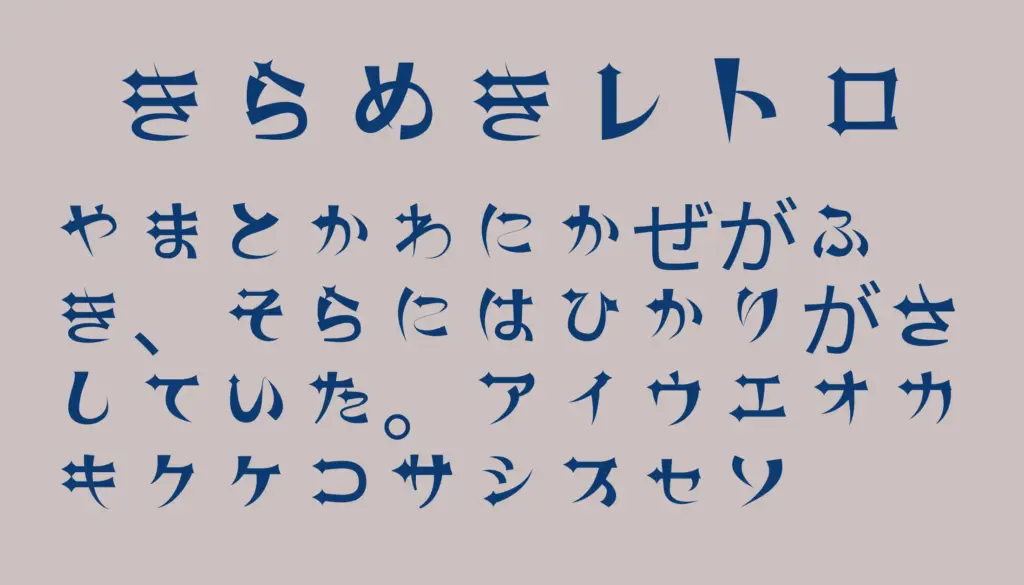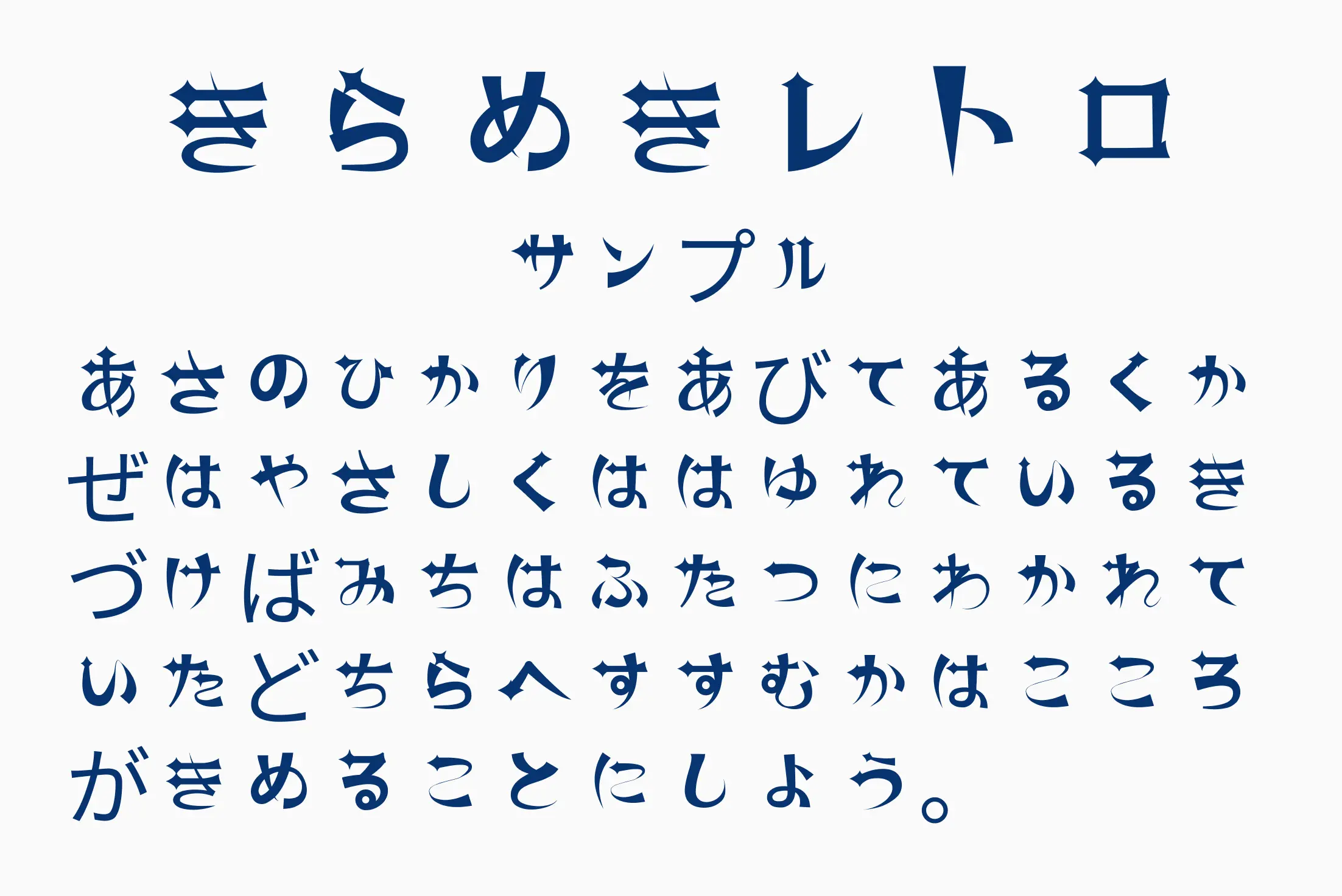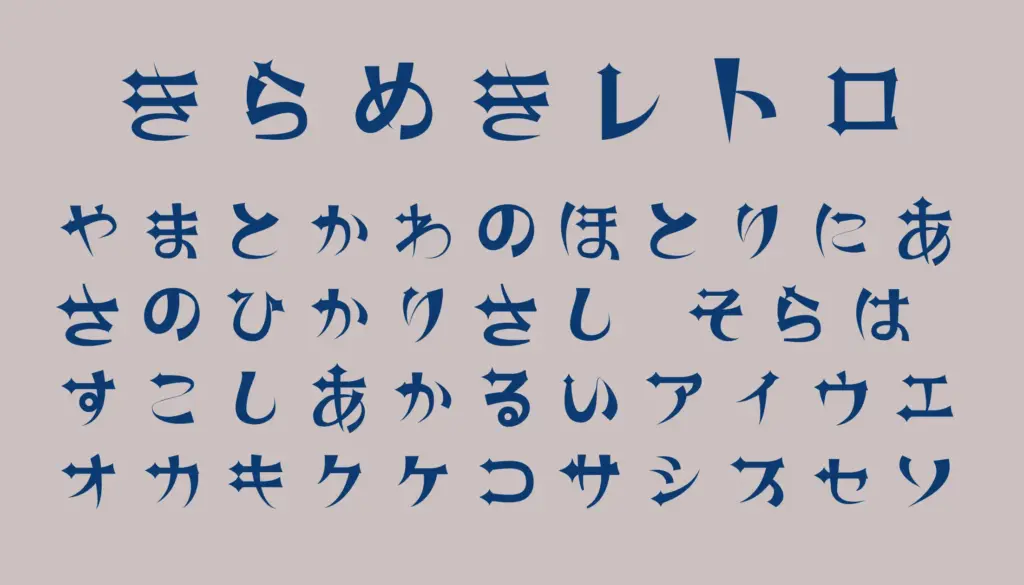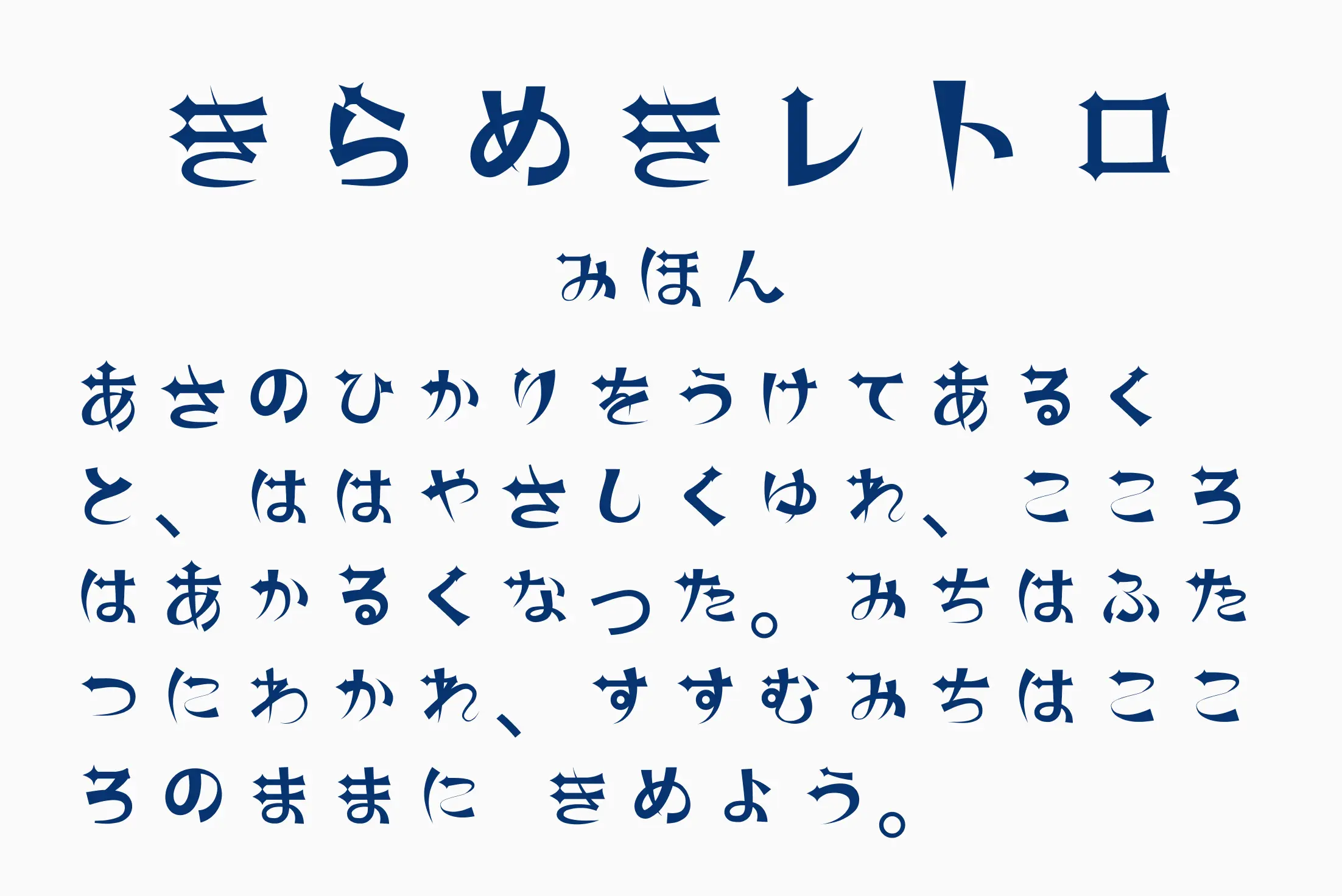
昭和のモダンデザインを彷彿とさせる、上品かつ印象的なレトロ風フォント。文字の端々に独特な装飾が施されており、タイトル・看板・メニュー・雑誌風デザインなどにぴったりです。クラシカルながらも遊び心のあるスタイルで、目を引くビジュアルを演出できます。
きらめきレトロ
| 収録文字 | ひらがな・カタカナ(濁点・半濁点・小文字なし) |